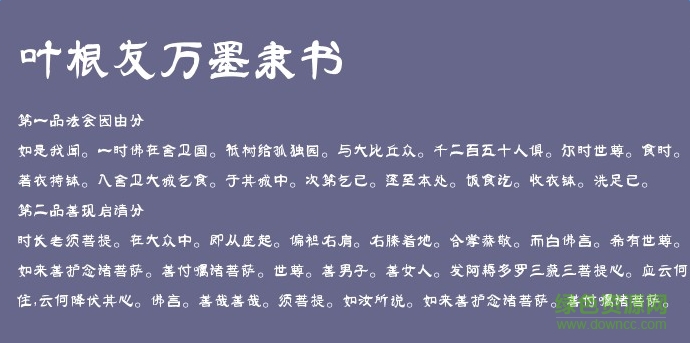
葉根友萬墨隸書
葉根友萬墨隸書是一款葉根友系列典型隸書風(fēng)格字體軟件,字體筆畫看似隨意卻別有一番韻味,于一絲潦草中透露著滿滿的放浪不羈,更多好看字體下載盡在綠色資源網(wǎng)!
葉根友萬墨隸書是一款大氣而不失遒勁的隸書字體,在所有葉根友隸書字體中,這是最近幾年新創(chuàng)意出的一款隸書風(fēng)格毛筆字體,相同風(fēng)格的有特隸簡體、蠶燕隸書等。
該字體筆畫隨意放浪不羈,字體比較時尚可愛,給人非常脫俗大方的感覺,非常的好看!喜歡就來下載使用吧!